텍스트 활자체 VS. 디스플레이 활자체
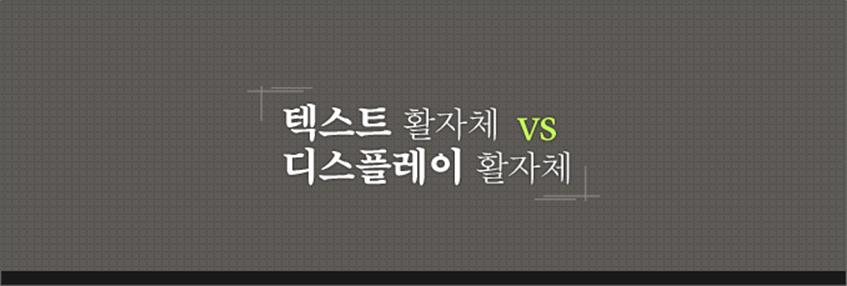
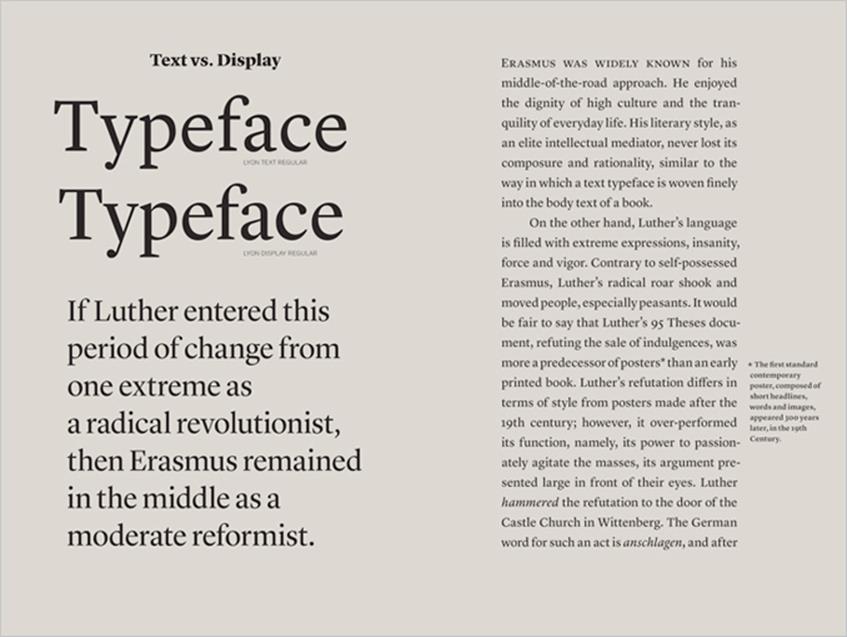
“활자가족 구성원의 이름을 볼드, 레귤러, 라이트 대신, 사용자들이 어느 크기에 적용하면 좋을지 정보를 줄 수 있도록 6, 12, 18, 48 등으로 붙이면 어떨까요? 라틴 알파벳 활자체에서 간혹 그러기도 하지만요.”, “아예 매체 별로 최적화해서, 이를테면 명조 매거진, 명조 간판 등으로 패밀리 네임을 붙일 수도 있겠네요.” 새로운 한글 활자체를 기획하는 회의에서 얼마 전 오갔던 대화 내용이다. 보다 아늑하고 풍요로운 타이포그래피적 색채감을 위해, 특정한 환경에 최적화할 수 있도록 활자가족을 점차 역동적으로 구성해가는 것이 최근 활자체 디자인의 추세 중 하나다.
이러한 추세에 발맞추어 나타난 대표적인 현상 중 하나가, 크기의 범주별로 폰트를 각각 디자인하는 활자가족의 구성이다. 이른바 ‘크기에 따른 착시 교정용 폰트(optical size font)’라고 부른다. 사이즈군별로, 이를테면, 디스플레이(표제), 서브헤드(소제목), 텍스트(본문), 캡션(각주) 등 각각의 크기에 맞게 특화될 수 있도록, 활자가족의 구성원들을 모두 달리 디자인하는 것이다.
90년대 초반 그런지 폰트(grunge font)라 불리는 일군의 시끄러운 디지털 활자체의 범람, 탈선적이고 과도한 형태가 남발되던 현상을 뒤로 하고, 이제는 디지털 활자의 시대도 차츰 진정기의 국면에 접어든 듯 하다. 일상에서도 격변하는 시대의 빠른 흐름이 웰빙의 각성을 불러왔듯, 활자체, 특히 본문 기본형 활자체에서는 바야흐로 활자의 ‘슬로우푸드’ 시대라 불릴 법한 새로운 흐름이 등장했다.
타이포그래퍼들의 정교하고도 까다로운 요구를 충족시키고, 동시에 독자에게 쾌적한 지면 환경을 제공할 수 있도록 폰트들은 특화되어 가고 있다. 활자는 그 크기에 따라 시각적인 화학 작용이 일어난다. 6포인트 이하 작은 크기에서 제대로 기능하는 활자체가 있고, 24포인트 이상, 심지어 간판만한 커다란 크기에서 제대로 기능하는 활자체가 있다. 대체로 9~12포인트의 크기에 최적화된 활자체를 텍스트 활자체, 24포인트 이상의 크기에 최적화된 활자체를 디스플레이 활자체라고 부른다.
크게 사용하는 디스플레이 활자체는 유려하고 섬세하며 정교하게 디자인한다. 그리고 시각적 힘이 강해야 한다. 작은 크기에서는 정교한 디테일이 도리어 가독성에 해를 입힌다. 크게 확대해 보면 거칠고 이상하게 보이는 형태적 형질이 오히려 작은 크기에서는 활자체를 원만하게 기능하도록 만든다. 디스플레이 활자체는 보는 영역을, 텍스트 활자체는 읽는 영역을 좀 더 비중 있게 관할한다. 디스플레이 활자체는 날렵한 형태감을 가지도록, 폭을 늘씬하게 좁히고 굵은 부분과 가는 부분의 콘트라스트를 강조한다.
텍스트 활자체는 안정된 견고함을 가지도록, 폭을 편안하게 넓히고 콘트라스트를 줄여 두툼하게 만든다. 폭과 콘트라스트 등 전체적인 차이뿐 아니라, 세부의 형태, 속 공간의 분배, 공간의 비례 등이 모두 미세하게 조금씩 달라진다. 디스플레이 활자체는 정교하고 매끈하게 다듬어지는 반면, 텍스트 활자체는 간소하면서도 분명하게 분절된 절도 있는 형태를 가진다.
그러므로 텍스트 활자체가 긴 본문에서 제대로 기능하도록 하려거든, 미려한 형태를 포기할 수 있는 용기도 필요하다. 텍스트 활자체는 본문의 콘텐츠를 겸손하게 중재해야지, 자신을 뽐내선 안 된다. 그렇다고 시무룩하거나 고루한 태도를 보인다면, 그 활자체는 텍스트 활자체로서 훌륭한 자질을 갖추었다고 할 수 없다. 건강한 활력과 생기가 넘치도록 본문 텍스트를 북돋워 주어야 한다. 그러기 위해 텍스트 활자 디자이너는 자신의 에고가 작업을 방해하지 않도록 늘 경계해야 한다. 스스로를 드러내고자 하는 유혹, 영향력을 행사하고자 하는 유혹으로부터 자신을 지키는 강건함은, 텍스트 활자 디자이너가 가져야 할 미덕이다.
텍스트 활자를 연구하고 디자인하는 공간에 단 한 인물의 초상만을 걸도록 한다면, 나는 그 주인공으로 에라스뮈스를 택하고 싶다. 에라스뮈스에게 경의를 표하고자 해서가 아니다. 그의 초상은 이 공간에서 인문주의자인 에리스뮈스적 정신의 작업이 이루어진다는 표식인 것이다. 이곳은 거칠고 선동적인 언어가 아닌, 세밀하고 사색적인 언어로서 독자를 이해시키는 중재의 즐거움이 이루어지는 공간이라는 의미이다. 이곳에서 만들어지는 활자체는 딱딱한 학문에도 세련된 재치, 온화한 유머, 영리하고 선량한 수완을 잃지 않도록 하는 시각적 말투와 태도를 입히게 될 것이다.
한편, 에라스뮈스의 대척점에 선 인물이 한 명 있으니, 그는 혈기 왕성한 마르틴 루터이다. 에라스뮈스와 루터는 실제로 논쟁을 벌였다. 그들은 당시 첨단 기술이었던 인쇄술 발명의 놀라운 파장을 가장 드라마틱하게 주도했던 주역들이다. 에라스뮈스와 루터는 인쇄소를 통해 서로 싸웠다.
인쇄술 발명이라는 미디어 혁명은 언어혁명과 종교혁명으로 이어졌다. 이 변동의 시기, 루터가 광포한 혁명가로서 한쪽 극단에서 등장했다면, 에라스뮈스는 중간에 서서 온건한 개혁가로 남았다. 에라스뮈스는 어느 편에도 서지 않는 중립으로 유명했다. 그리고 그는 귀족적 문화의 품위와 일상의 평온함을 향유했다. 엘리트적 중재자로서의 그의 문체는 고요한 평정심과 이성을 잃지 않는다. 책의 본문에 곱게 직조된 텍스트 활자체의 역할이 그렇듯 말이다.
반면 루터의 언어는 극단적 표현과 광기, 건장한 힘과 정력으로 가득 차 있다. 차분한 에라스뮈스와 달리 루터의 과격한 포효는 민중, 특히 농민을 흔들고 움직였다. 면죄부 판매를 규탄하는 루터의 95개조 반박문은 인쇄된 서적의 초창기 모습이라기보다는, 차라리 포스터의 전신이라고 보는 편이 타당할 것이다. 짧은 표제용 문구나 단어, 강렬한 이미지로 구성된 본격적인 포스터는 사실 세 세기나 지난 후인 19세기에 등장했다.
산업혁명으로 경쟁이 과열되면서 광고가 전면에 등장하고, 기술적으로는 다색석판화의 자유롭고 현란한 표현이 가능해 진 배경을 등에 업은 후의 일이다. 95개 문항의 텍스트로만 이루어진 루터의 반박문은 19세기 이후의 포스터와 양식적으로는 큰 차이가 나지만, 대중의 눈앞에 펼쳐져 그들을 격정적으로 선동하는 힘에 있어서는 그 이상의 기능을 수행했다. 루터는 비텐베르크의 교회 문 앞에 이 반박문을 힘차게 ‘박았다.’ 유럽 인쇄술 초창기의 종이는 동양의 한지처럼 얇고 가볍지 않았다.
그리고 당시에는 종이를 벽에 고정시킬 접착용 테이프도 없었다. 그는 망치로 못을 두드려야 했다. 그렇게 이 조항들이 빼곡히 조판된 인쇄물을 힘껏 때려 박았다. 이 행동을 독일어로는 안슐라겐(anschlagen)이라고 표현한다. 그리하여 안슐락(Anschlag)이라는 단어는 ‘문자로 선포하는 포스터’라는 의미로도 사용되기 시작했다. 루터의 문체는 포스터에 사용되어 시선을 사로잡아야 하는 디스플레이 활자체의 역할을 닮았다.
루터의 활자는 대중을 향했고, 에라스뮈스의 활자는 귀족을 향했다. 포스터는 보고자 하는 의도가 없더라도 강제적으로 눈 앞에 보여지지만, 책은 덮인 표지를 직접 펼치는 적극적 행동과 보고자 하는 의지가 있어야 접근에 이를 수 있고, 나아가 긴 시간을 들여 읽고자 하는 의지가 있어야 그 내용이 전달되고 흡수된다. 책이라는 매체는 그 태생부터 어느 정도 엘리트 지향적이다. 타이포그래퍼이자 활자체 디자이너인 얀 치홀트는 훌륭한 텍스트 활자체로 잘 조판된 지면의 진가는 엘리트만 알아볼 수 있다고도 했다. 공을 들인 텍스트 활자체에 깃든 가치를 향유할 수 있는 사람은 많지 않지만, 그렇게 만들어진 활자체는 간접적이면서도 오래, 널리 지속되는 영향력을 가진다.
활자는 정신을 담아내면서도, 그 자신은 물질적 육신을 가지고 있다. 지난날의 인문주의적 출판업자들은 그들이 귀중하게 여기는 정신을 아름다운 책의 육신으로 화하도록 온갖 노력을 기울였다. 그 육신의 일부인 활자를 만들어 낼 다재다능한 활자 제작자들은 그들의 중요한 인적 자산이었다. 베네치아의 알두스 마누티우스에게는 프란체스코 그리포가 있었고, 리옹의 장 드 투른과 안트베르펜의 크리스토프 플랑탱에게는 로베르 그랑종이 있었다. 인문주의를 새 시대의 정신에 담는 출판인들의 르네상스, 그 영광과 번영은 아름다운 활자로써 인쇄된 기록으로 남아 전해져 내려오며 빛난다.
텍스트 활자를 통해 정신은 인쇄된 육신을 입는다. 육체적 외형이란 내면을 반영하고, 또 정신을 해석하기도 한다. 타이포그래피는 불가피하게 텍스트를 해석한다. 활자의 육신과 텍스트의 정신은 책에서 공존한다. 그러니 텍스트 활자체 디자이너는 정신에 침몰하느라 에너지가 가득한 물질적 세계의 생기를, 육체적 삶의 즐거움을 잃는 우를 범해서는 안 된다. 에라스뮈스의 「우신예찬」에서 어리석음의 여신은 이렇게 마지막 인사를 남긴다. “그러니 안녕히, 손뼉을 치고, 열정적으로 포도주를 마시며 살아가세요.”